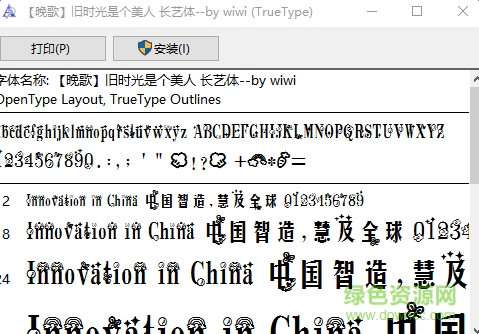
舊時(shí)光是個(gè)美人字體是一款很好看的電腦個(gè)性字體,這款字體寫(xiě)出來(lái)的字是很美觀的,而且有著別的字體沒(méi)有的魅力,相信很多朋友們都會(huì)喜歡這款字體的,歡迎有需要的朋友來(lái)綠色資源網(wǎng)下載。
舊時(shí)光是個(gè)美人字體是真的很不錯(cuò),因?yàn)槠洫?dú)特的魅力,用于藝術(shù)方面是最合適不過(guò)的,喜歡的朋友可以隨時(shí)來(lái)綠色資源網(wǎng)下載。